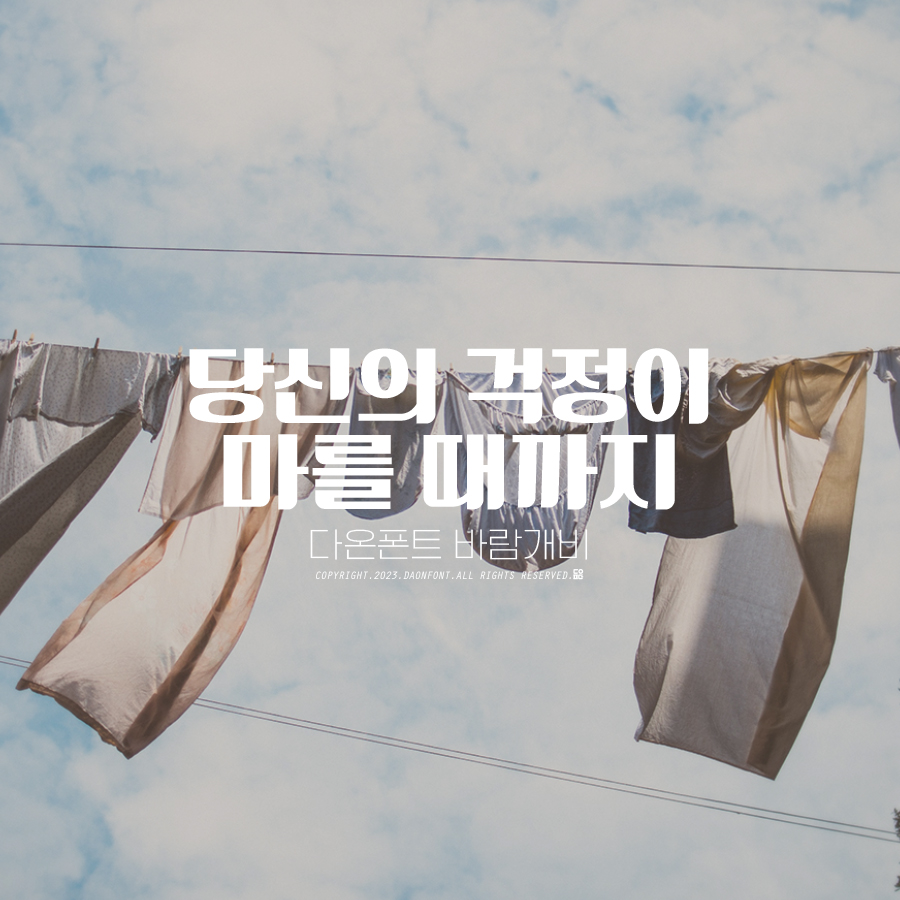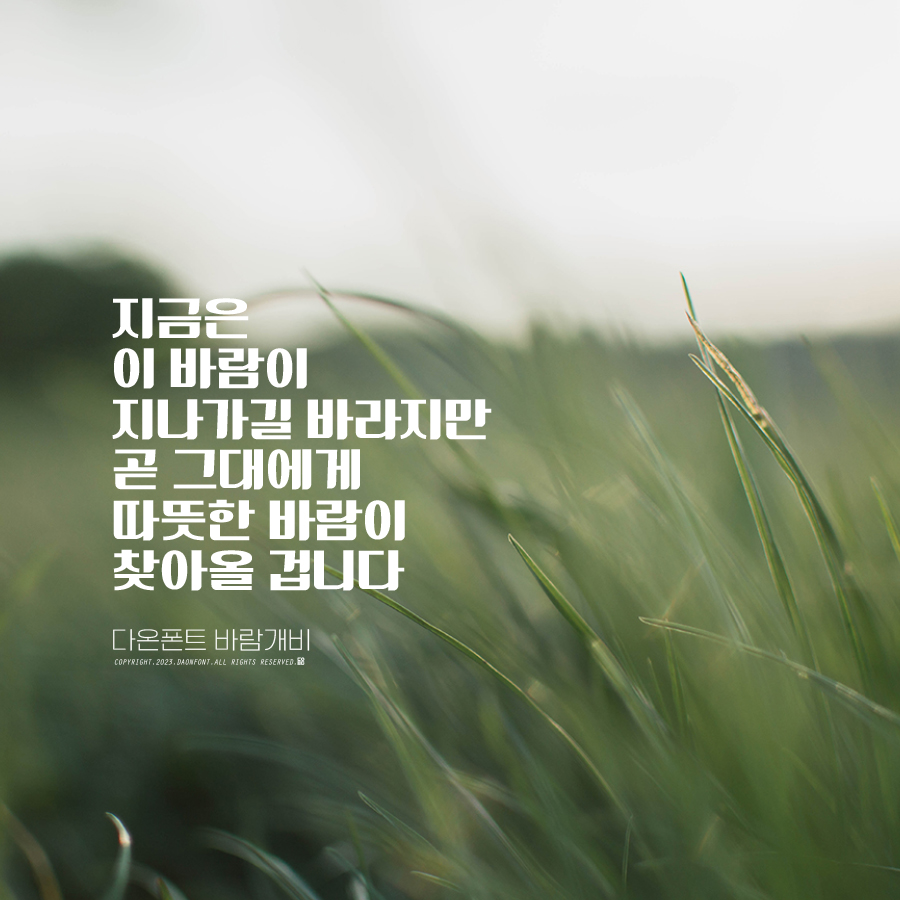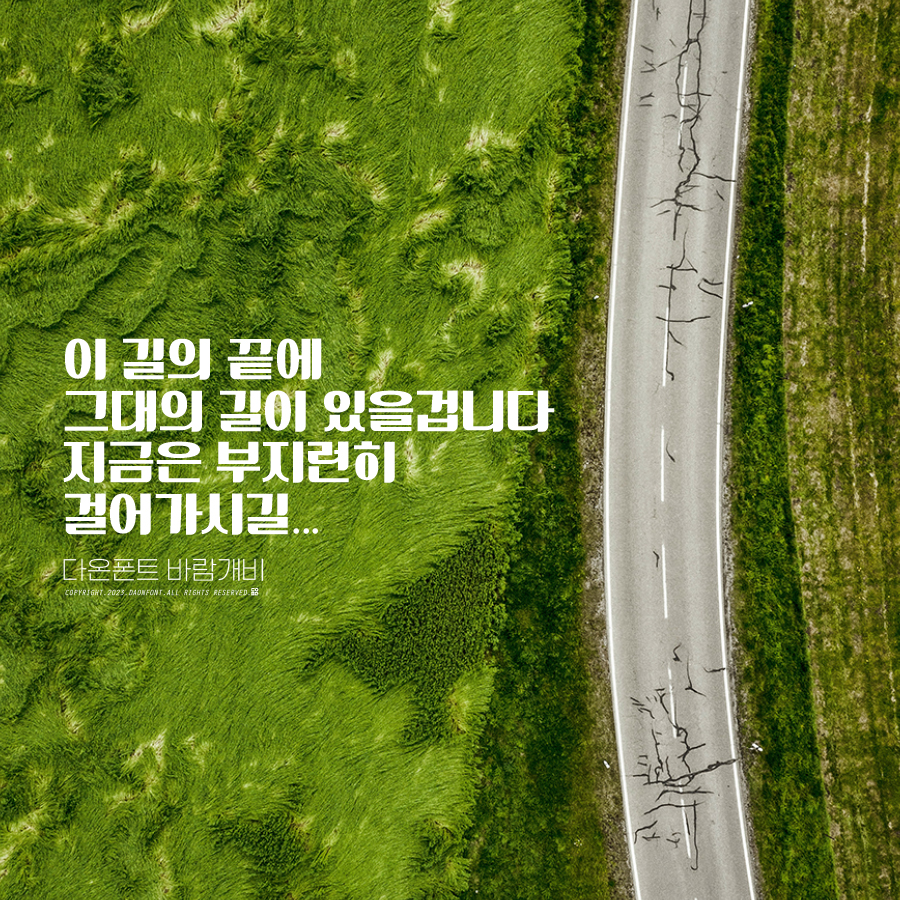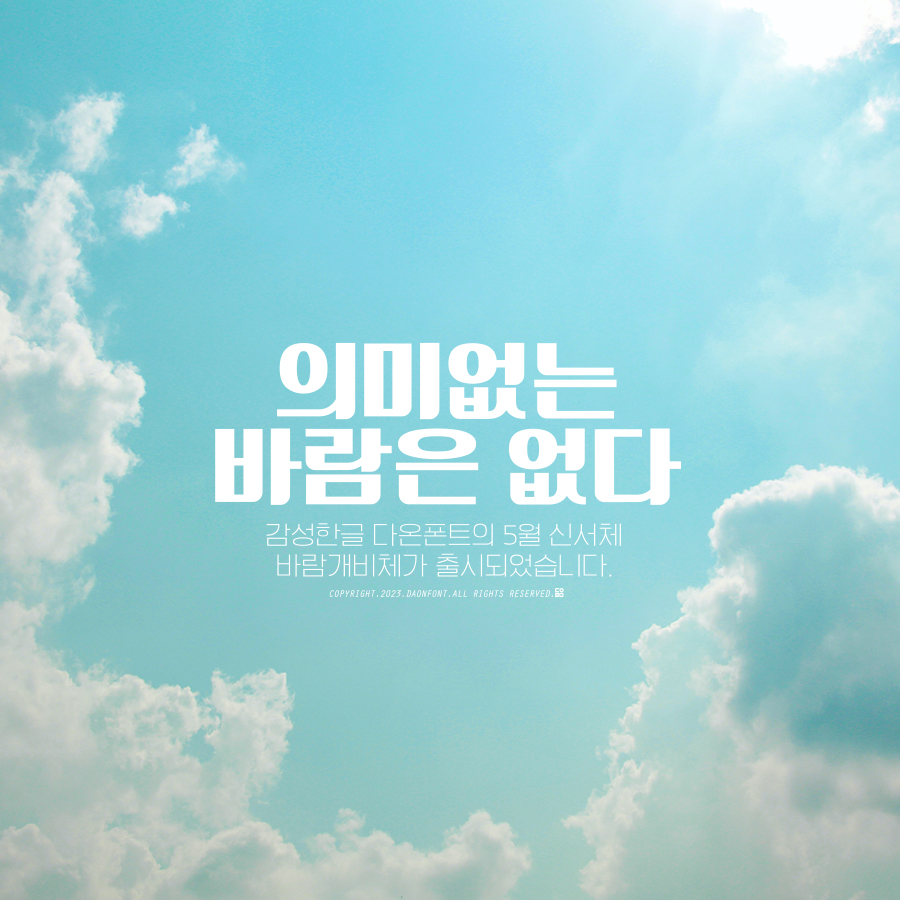
5월 신서체 다온폰트 바람개비 출시 안내
다온폰트 5월 세번째 다온폰트 신서체,
다온폰트 바람개비가 출시되었습니다.
다온폰트 바람개비는 제목용서체로 제작되었으며,
한글 2780자와 영문, 숫자, 특수문자, 딩벳셋트로 구성된 서체입니다.
가로줄기와 세로줄기의 차이가 있어 다양한 용도로 사용하실 수 있습니다.